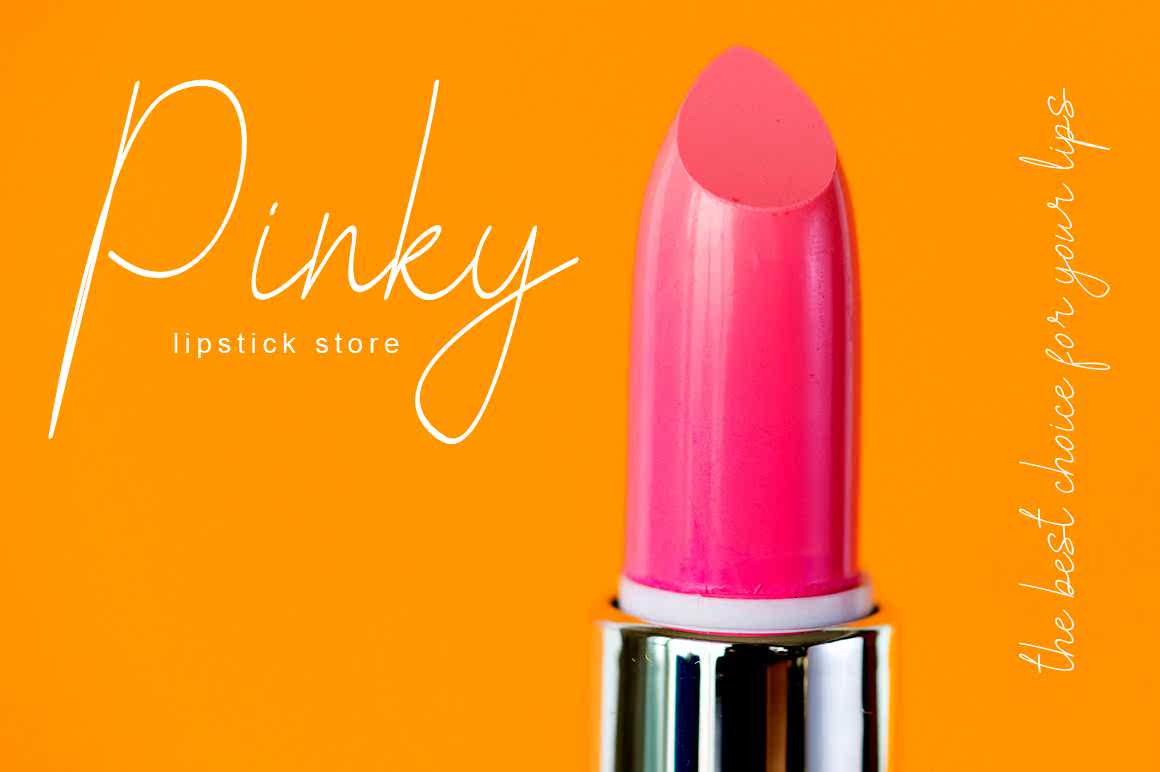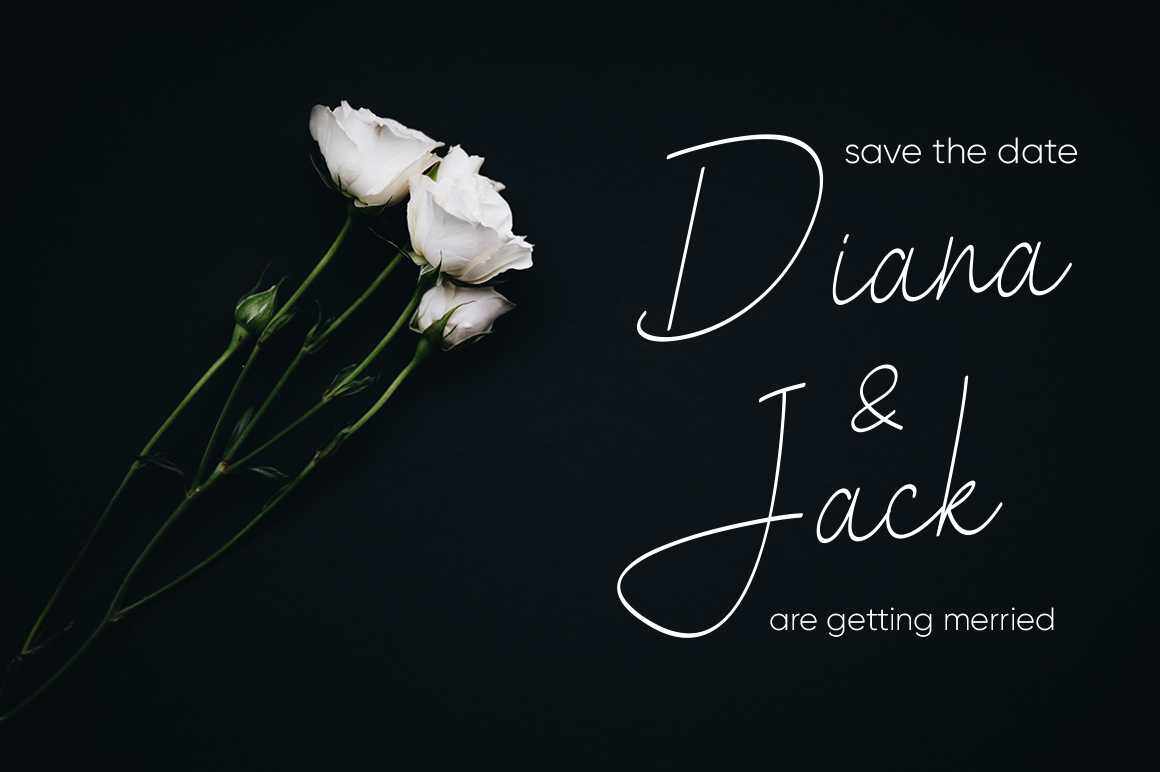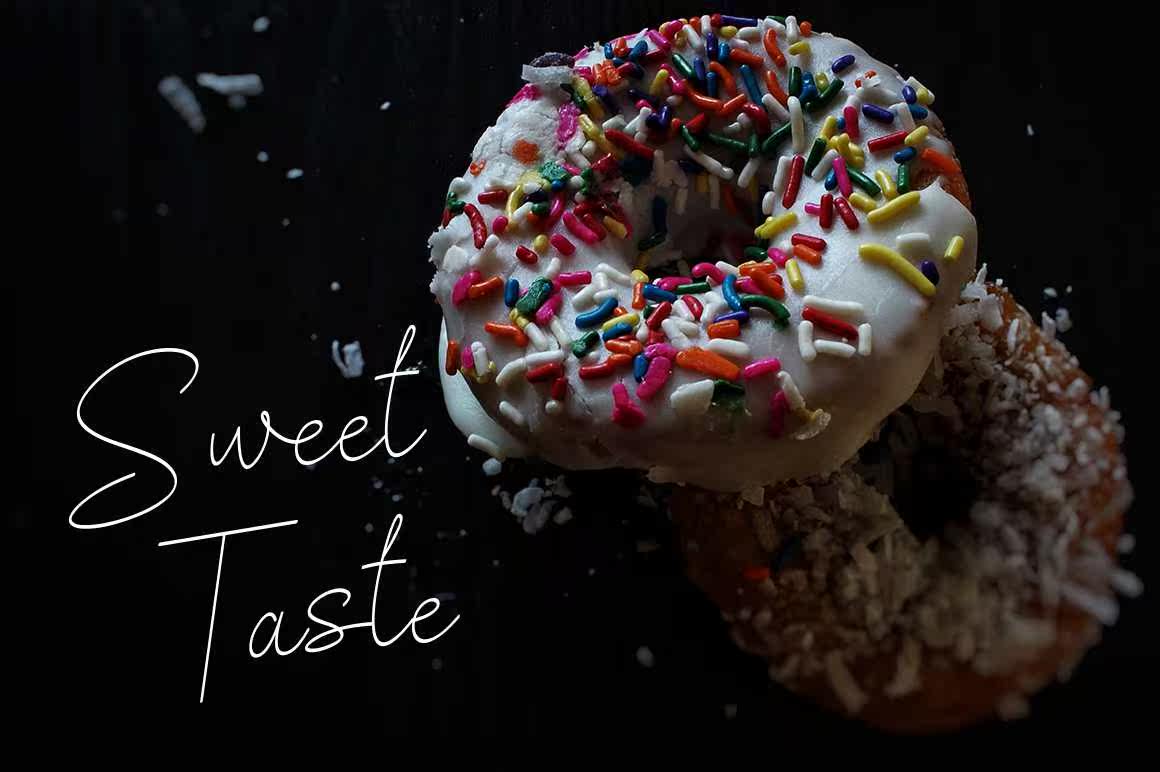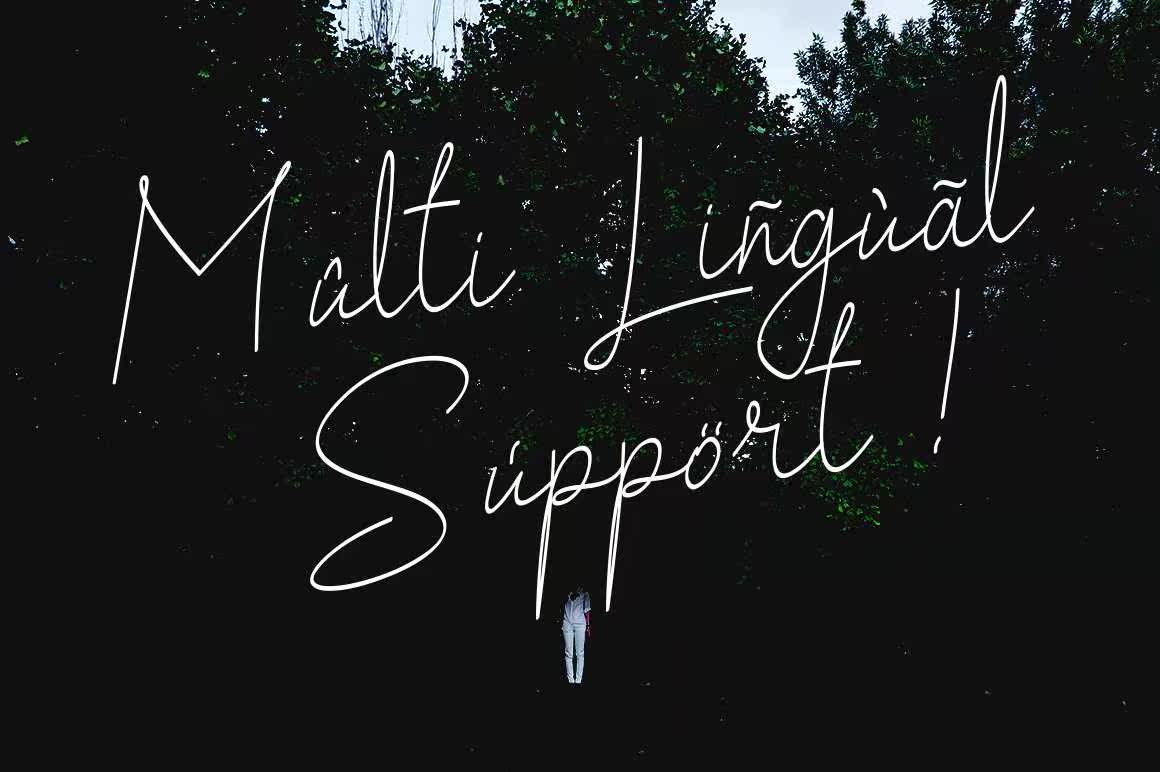
Salhenaastylishhandwrittenfont–一个带有手写体和手写体样式的现代和新鲜脚本使此Font看起来优雅、自然、风格完美,适合所有需要手写的项目。Salhenaastylishhandwrittenfont–一个带有手写体样式和手写体样式的现代和新鲜脚本使此Font看起来优雅、自然,对于某些需要手写品味的项目来说,风格是完美的。